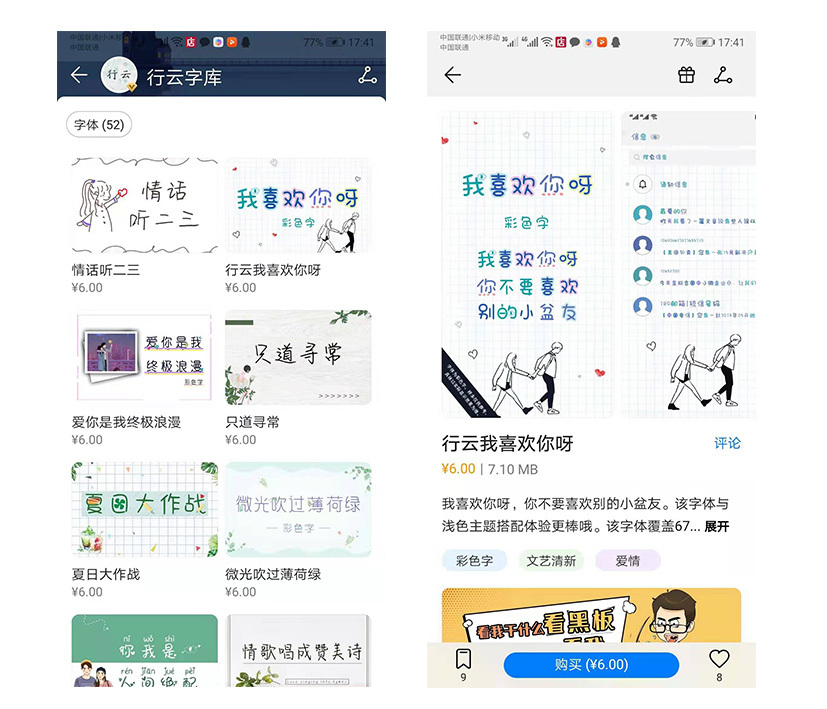
字库品牌:行云字库
【华为主题官方认证设计师】
简介:行云字库,是华为主题官方认证的设计师。字体主要偏向于清新风格,
包含手写字体,1568194965(1).png拼音字体,彩色字体等。行云字库是一家专业从事字体设计、字库产品开发的团队。
字体信息:
1.    字体数量:52款
3.    字体种类:手写字体、拼音字体、彩色字体
作品信息: